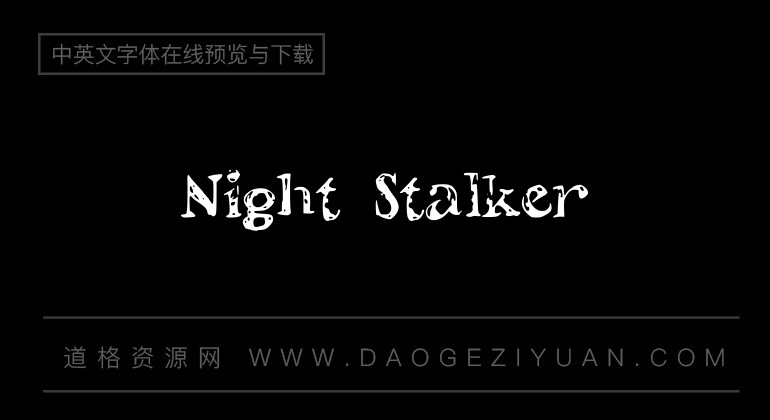
Night Stalker
Night Stalker 是一款由 Font Fabric 公司设计的字体,它拥有独特的设计,具有抽象的外观和抽象的线条,它的字符具有丰富的纹理,使用它可以创造出独特的文字设计。它具有细节丰富的外观,可以帮助您创造出更有趣的文字设计。它有多种字体样式,包括细体、粗体、斜体、带有阴影的字体等,可以满足您的不同需求。
Night Stalker是一款非常不错的手写艺术字体,具有很好的视觉感,适合于文化类的宣传设计、商业类品牌的广告和产品包装设计以及个性化文字排版等较多场景。